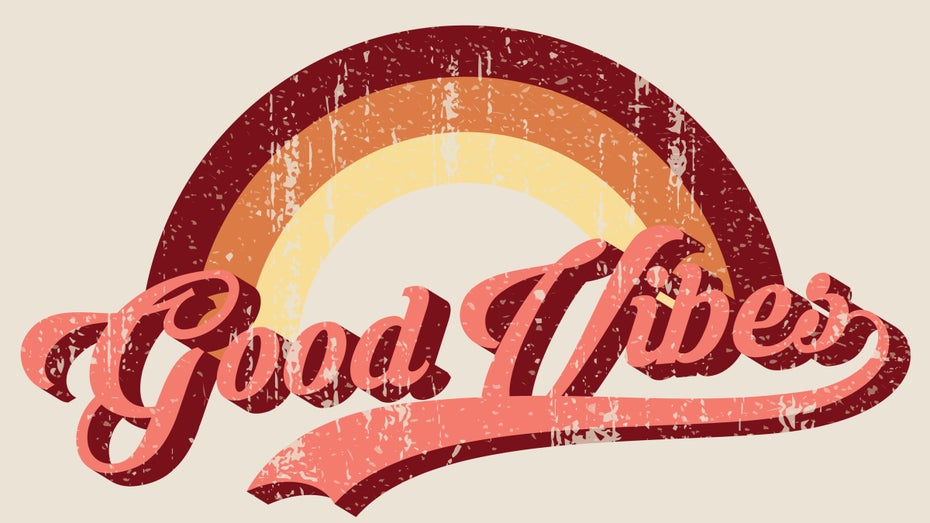
Die Macht der Vergangenheit: Wie Vintage-Typografie Marken emotional auflädt
Vintage- oder Retro-Fonts transportieren Emotionen. (Grafik: EnkaArt/Shutterstock)
Nostalgie kann einen erheblichen Einfluss darauf haben, wie attraktiv Produkte für Kunden erscheinen. Das zeigt eine Studie aus dem Journal of Marketing, durchgeführt von Forschern der University of Newcastle in Australien.
Dabei wurde entdeckt, dass der Einsatz einer Vintage-Schriftart auf Produkten zahlreiche positive Effekte haben kann. Die Forscher fanden heraus, dass die Schriftart eine wesentliche Rolle bei der Wahrnehmung eines Produkts spielt.
„Obwohl Typografie in Marketing und Werbung oft als ein sekundäres Element betrachtet wird, hat sie weitreichende Auswirkungen über die bloße Ästhetik hinaus. Sie beeinflusst entscheidend, wie Menschen denken, fühlen, sich verhalten, wie sie Marken bewerten und Entscheidungen treffen“, erklärt Alicia Kulczynski, eine Autorin der Studie.
Nostalgie sorgt für positive Emotionen
In ihrer Studie stellten die Forscher fest, dass Vintage-Typografien bei Konsumenten das Phänomen der „Vintage-Anämie“ auslösen können, eine tiefe emotionale Bindung zur Vergangenheit.
Kunden assoziieren alte Zeiten oft mit Sicherheit, Wohlstand, Qualität und Glück, und das unabhängig von ihren tatsächlichen Erfahrungen. Die Anwendung von Vintage-Schriftarten kann dazu beitragen, diese Werte auf ein Produkt zu übertragen.
Margurite Hook, eine Mitautorin der Studie, erklärt: „Unsere Forschungsergebnisse deuten darauf hin, dass Verbraucher Produkte einer Marke als sicherer wahrnehmen, wenn sie eine Vintage-Anämie verspüren, nachdem sie Vintage-Typografie in Werbungen, Markenlogos oder auf Verpackungen gesehen haben.“
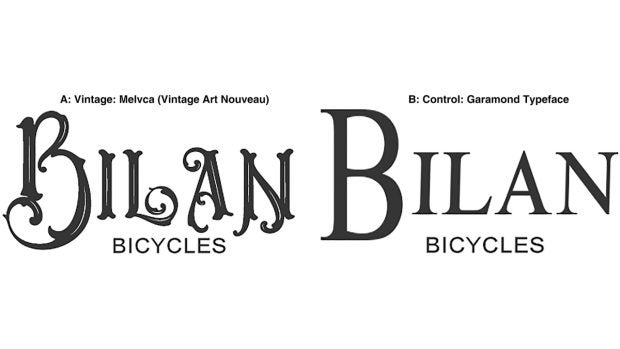
Auch bei Fahrrädern kann eine Vintage-Schriftart funktionieren. (Grafik: Typography Talks: Influencing Vintage Anemoia and Product Safety Perceptions with Vintage Typography / Journal of Marketing)
Vintage-Schriftart funktioniert nicht immer
Obwohl Vintage-Schriftarten eine starke emotionale Verbindung zur Vergangenheit hervorrufen können, sind sie nicht in jedem Kontext das Allheilmittel. Damit sie ihre volle Wirkung entfalten, müssen bestimmte Bedingungen erfüllt sein.
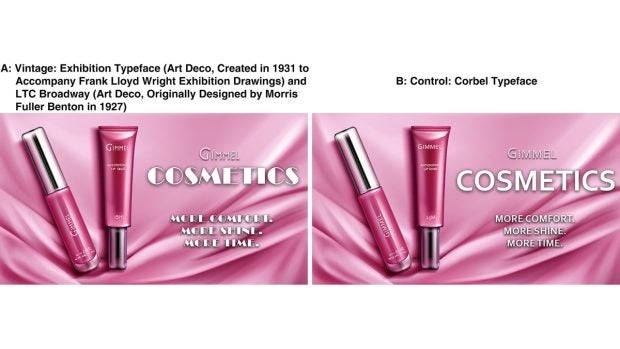
Alt wirkende Schriftarten haben emotionale Ladung. (Foto: Typography Talks: Influencing Vintage Anemoia and Product Safety Perceptions with Vintage Typography / Journal of Marketing)
So sind diese Schriftarten bei futuristischen Produkten weniger effektiv, da sie selbst keinen Bezug zur Vergangenheit herstellen. Ebenso reicht es nicht aus, lediglich das Gründungsjahr einer Marke hervorzuheben. Wichtiger ist der Stil der Schriftart selbst.
Trotz dieser Einschränkungen können Vintage-Schriftarten ein wirkungsvolles Werkzeug in der Marketingstrategie sein.